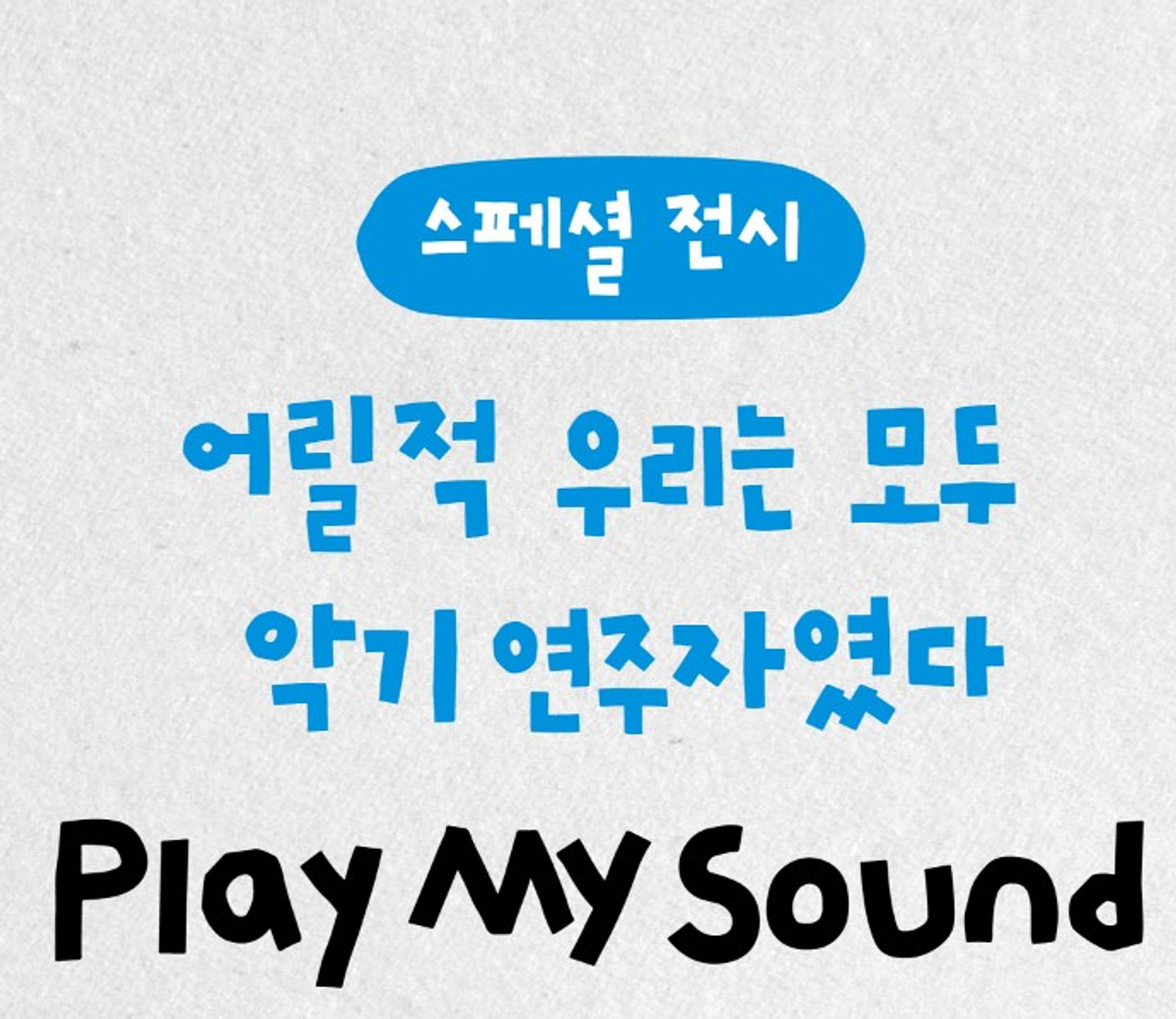
밑미 홈페이지에서 보게 된 폰트인데 폰트찾기 하니까 비슷하고 다른 폰트가 나오네요ㅠㅠ 혹시 무슨 폰트인지 아시는 분 있다면 알려주세요ㅠㅠ!!
타이포 돈키호테
제일 비슷한 폰트는 이것이나, 첨부 이미지처럼 '오' 글자가 다르게 쓰인걸 보면 일러스트로 폰트조정하거나 제작한 폰트로 보입니다.https://www.sandollcloud.com/font/15590/Typo_DonQuixote